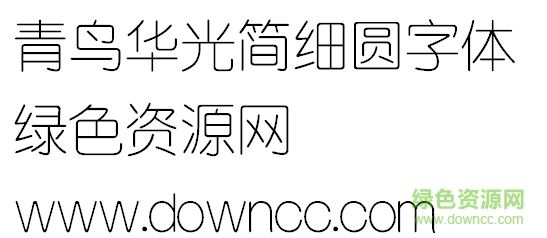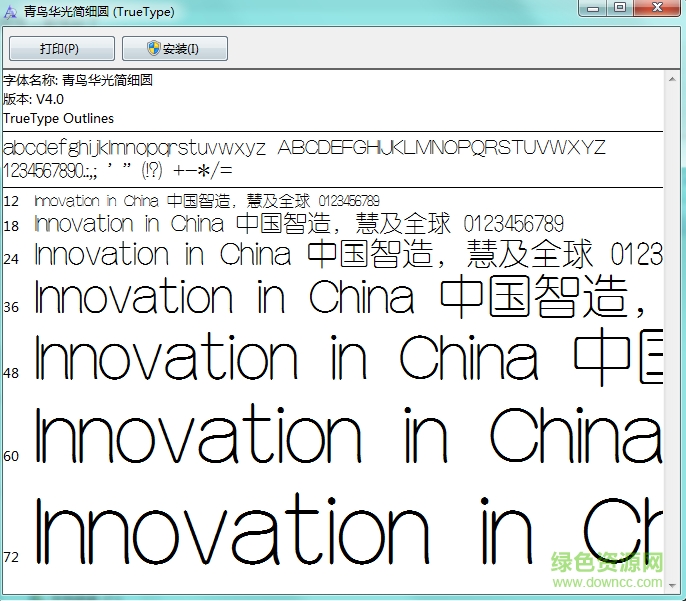
青鳥(niǎo)華光簡(jiǎn)細(xì)圓是一款細(xì)線簡(jiǎn)體,有著簡(jiǎn)潔優(yōu)美的線條,規(guī)整大方的造型,給人書(shū)寫(xiě)和閱讀好感,如果你喜歡,來(lái)綠色資源網(wǎng)下載準(zhǔn)沒(méi)錯(cuò)!
青鳥(niǎo)華光簡(jiǎn)細(xì)圓承繼了細(xì)圓字體的簡(jiǎn)練清新,端正的筆畫(huà)矯健的筆觸,讓你的平面設(shè)計(jì)、廣告布局、排版編輯更令人印象深刻。
青鳥(niǎo)華光簡(jiǎn)細(xì)圓字體筆畫(huà)纖細(xì),結(jié)構(gòu)簡(jiǎn)單,字體結(jié)構(gòu)端正大方,整體效果非常出色,畫(huà)流暢,文字排版方面可以使用!